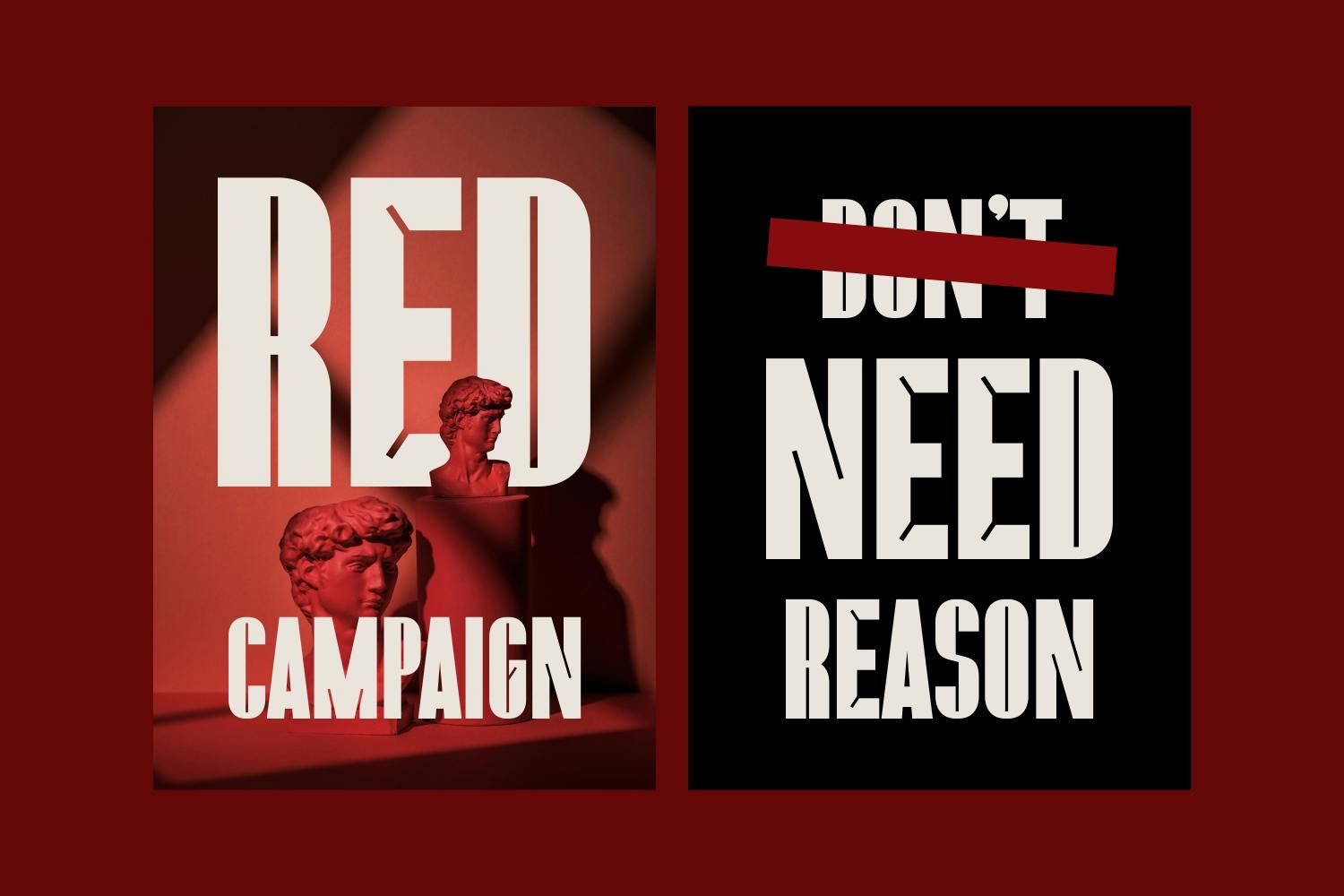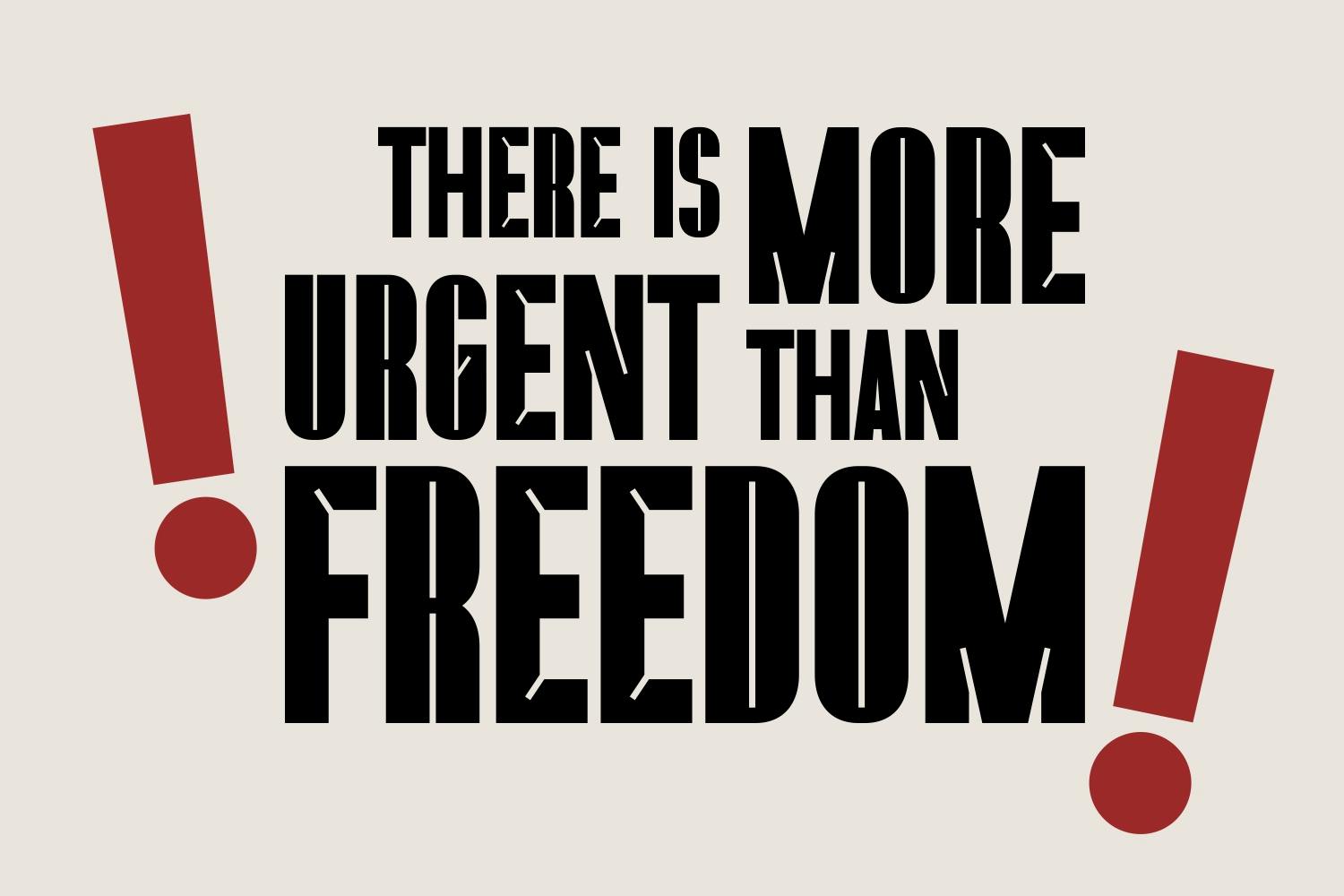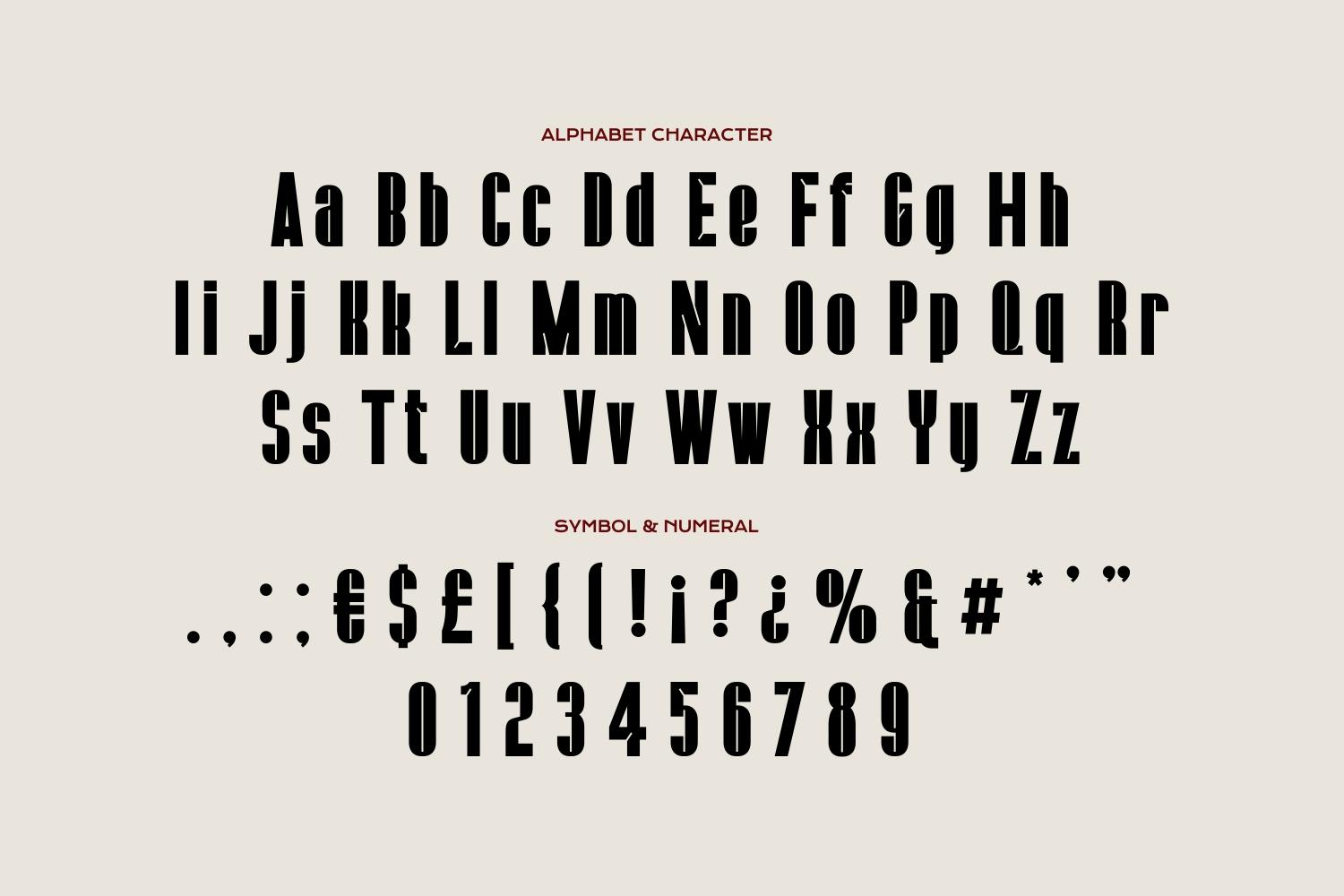
فونت Neobion یک فونت مدرن است که با منحنیهای نرم و سبک بصری خود میتواند جذابیت و elegance را در هر نوشتهای به نمایش بگذارد و کار شما را خیرهکننده و جذاب کند.
این فونت چندمنظوره در هر دو اندازه بزرگ و کوچک کار میکند و مناسب برای انواع مختلف پروژهها از جمله فونت نمایش برای عنوان، لوگو، دعوتنامهها، برندینگ، مجلات، عکاسی، کارت، بستهبندی محصولات، ماکت محصول، ماگ، پوستر، و هر نوع هدف تبلیغاتی است.